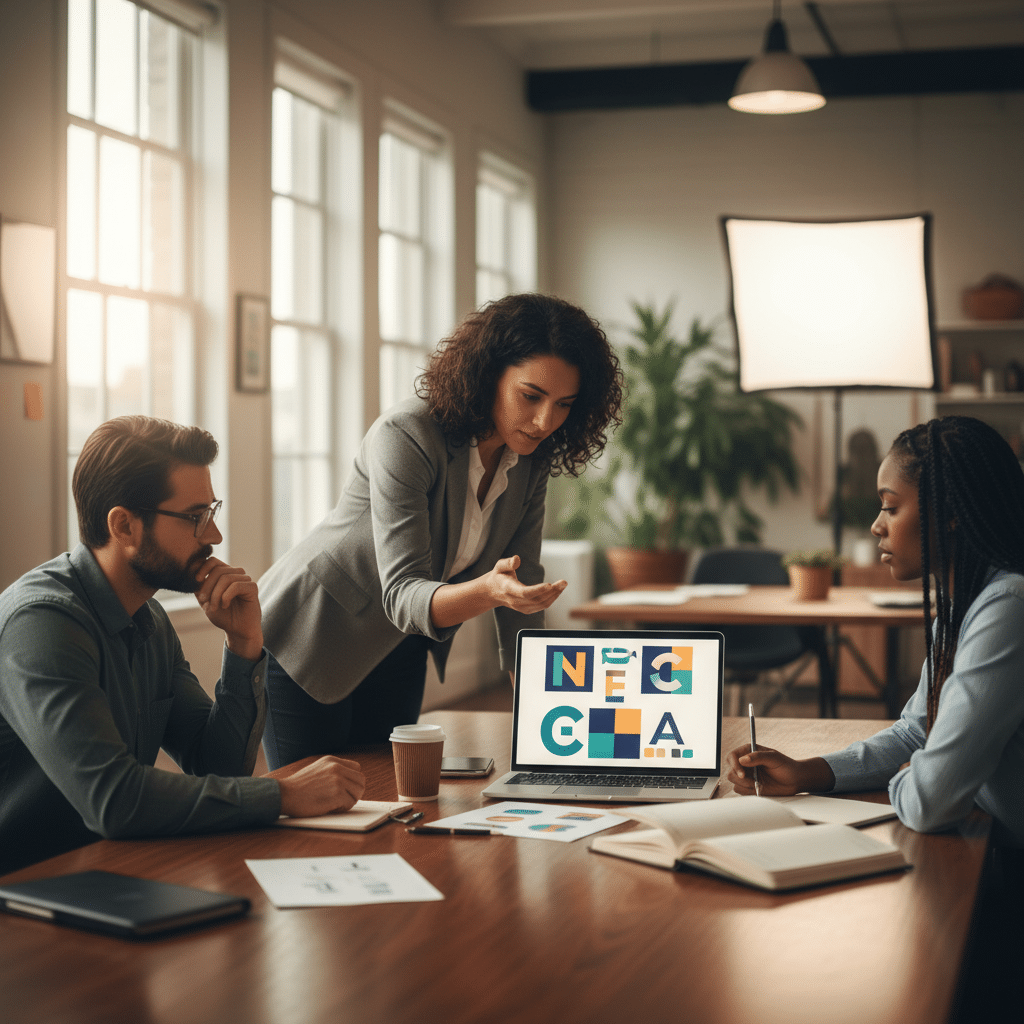
ฟอนต์เปลี่ยนแบรนด์! จิตวิทยาฟอนต์ที่ SME ต้องเลือกให้เป็น
การเลือกใช้ฟอนต์ไม่ใช่เพียงเรื่องของความสวยงามทางสายตา แต่เป็นเครื่องมือเชิงกลยุทธ์ที่ส่งผลกระทบโดยตรงต่อการรับรู้ของลูกค้า การตัดสินใจเลือก ฟอนต์เปลี่ยนแบรนด์! จิตวิทยาฟอนต์ที่ SME ต้องเลือกให้เป็น จึงเป็นศาสตร์ที่ผู้ประกอบการไม่ควรมองข้าม เพราะฟอนต์เปรียบเสมือน ‘น้ำเสียง’ ที่แบรนด์ใช้สื่อสารบุคลิกภาพ ค่านิยม และสร้างความน่าเชื่อถือในใจของผู้บริโภคได้ตั้งแต่แรกเห็น
แก่นสำคัญของจิตวิทยาฟอนต์
- ฟอนต์มีอิทธิพลต่ออารมณ์: รูปแบบของตัวอักษรสามารถกระตุ้นความรู้สึกที่แตกต่างกัน เช่น ความหรูหรา ความเป็นมิตร หรือความทันสมัย ซึ่งส่งผลต่อพฤติกรรมของผู้บริโภคโดยไม่รู้ตัว
- สร้างการจดจำและบุคลิกภาพ: ฟอนต์ที่เป็นเอกลักษณ์และสอดคล้องกับตัวตนของแบรนด์ ช่วยให้ลูกค้าสามารถจดจำแบรนด์ได้ง่ายขึ้นท่ามกลางคู่แข่งจำนวนมาก
- ยกระดับความน่าเชื่อถือ: การเลือกฟอนต์ที่เหมาะสมกับประเภทธุรกิจ สามารถเพิ่มความน่าเชื่อถือและความเป็นมืออาชีพให้กับแบรนด์ได้อย่างมีนัยสำคัญ
- สื่อสารคุณค่าของแบรนด์: ฟอนต์แต่ละประเภทมีความหมายแฝงที่สามารถสะท้อนถึงแก่นแท้และจุดยืนของแบรนด์ได้ เช่น ความสำเร็จ ความซื่อสัตย์ หรือความเป็นธรรมชาติ
ความสำคัญของจิตวิทยาฟอนต์ต่อแบรนด์ SME
สำหรับธุรกิจขนาดกลางและขนาดย่อม (SME) ที่มีทรัพยากรจำกัด การสร้างแบรนด์ให้แข็งแกร่งและเป็นที่จดจำคือความท้าทายที่สำคัญ จิตวิทยาฟอนต์ (Font Psychology) เข้ามามีบทบาทในฐานะเครื่องมือทางการตลาดที่ทรงพลังและคุ้มค่า เพราะฟอนต์คือองค์ประกอบแรกๆ ที่ลูกค้าสัมผัส ไม่ว่าจะผ่านโลโก้ บรรจุภัณฑ์ เว็บไซต์ หรือสื่อโฆษณาต่างๆ การเลือกฟอนต์ที่ถูกต้องสามารถสร้างความประทับใจแรกที่ยอดเยี่ยม และสื่อสารตัวตนของแบรนด์ออกไปได้อย่างชัดเจน
ฟอนต์ไม่ได้ทำหน้าที่เพียงแค่แสดงข้อความ แต่ยังทำหน้าที่ควบคุมการรับรู้และอารมณ์ของผู้ชมไปพร้อมกัน ฟอนต์ที่ดูหรูหราอาจทำให้ลูกค้ารู้สึกว่าสินค้ามีคุณภาพสูงและยินดีที่จะจ่ายในราคาที่แพงขึ้น ในทางกลับกัน ฟอนต์ที่ดูเป็นมิตรและเข้าถึงง่ายอาจช่วยสร้างความสัมพันธ์ที่ดีกับลูกค้าในธุรกิจบริการได้ ดังนั้น การทำความเข้าใจในศาสตร์นี้จึงเปรียบเสมือนการถือกุญแจสำคัญในการไขประตูสู่หัวใจของลูกค้าและสร้างความได้เปรียบในการแข่งขัน
การเลือกฟอนต์เปรียบเสมือนการเลือกเสื้อผ้าให้กับแบรนด์ หากเลือกได้เหมาะสมก็จะช่วยเสริมสร้างบุคลิกภาพให้น่าดึงดูดและน่าเชื่อถือ แต่หากเลือกผิด ก็อาจทำลายภาพลักษณ์ทั้งหมดได้ในพริบตา
ถอดรหัสความรู้สึกผ่านประเภทฟอนต์
ฟอนต์แต่ละประเภทมีโครงสร้างและลักษณะเฉพาะตัวที่ส่งผลต่อการตีความและความรู้สึกของผู้รับสาร การทำความเข้าใจความหมายทางจิตวิทยาของฟอนต์แต่ละกลุ่ม จะช่วยให้ SME สามารถเลือกใช้ฟอนต์ที่สื่อสารบุคลิกของแบรนด์ได้อย่างตรงจุด
ฟอนต์ Serif: สัญลักษณ์แห่งความน่าเชื่อถือและความหรูหรา
ฟอนต์ Serif คือฟอนต์ที่มี “ขีด” หรือ “เชิง” เล็กๆ อยู่ที่ปลายของตัวอักษร เป็นรูปแบบฟอนต์ที่มีประวัติศาสตร์ยาวนานและมักถูกใช้ในสื่อสิ่งพิมพ์แบบดั้งเดิม เช่น หนังสือพิมพ์ หรือหนังสือนวนิยาย ด้วยเหตุนี้ ฟอนต์กลุ่ม Serif จึงมักจะสื่อถึงความรู้สึก น่าเชื่อถือ, เป็นทางการ, หรูหรา, และ มีคุณภาพสูง แบรนด์ที่ต้องการสร้างภาพลักษณ์ที่ดูภูมิฐาน มั่นคง และเป็นที่ยอมรับ มักจะเลือกใช้ฟอนต์ประเภทนี้ ตัวอย่างเช่น ฟอนต์ Cotford Display Regular ที่ช่วยเสริมสร้างความสัมพันธ์และความไว้วางใจให้กับแบรนด์ได้เป็นอย่างดี
เหมาะกับธุรกิจ: แบรนด์แฟชั่นระดับสูง, ธุรกิจบริการที่เน้นความเป็นมืออาชีพ (เช่น สำนักงานกฎหมาย), สินค้าลักชัวรี, ธุรกิจโรงแรม, หรือสถาบันการเงิน
ฟอนต์ Sans-Serif: เสียงสะท้อนของความทันสมัยและความเรียบง่าย
“Sans” เป็นภาษาฝรั่งเศส แปลว่า “ไม่มี” ดังนั้น Sans-Serif จึงหมายถึงฟอนต์ที่ “ไม่มีเชิง” นั่นเอง ฟอนต์ประเภทนี้มีลักษณะที่ดูสะอาดตา เรียบง่าย และทันสมัย ทำให้เป็นที่นิยมอย่างสูงในยุคดิจิทัล โดยเฉพาะบนหน้าจอคอมพิวเตอร์และสมาร์ทโฟน ฟอนต์ Sans-Serif สื่อถึงความ ทันสมัย, ก้าวหน้า, เข้าถึงง่าย, และ ซื่อสัตย์ ฟอนต์ในกลุ่มนี้ยังแบ่งย่อยได้อีก เช่น Geometric Sans-Serif อย่าง Gilroy Bold ที่มักจะสื่อถึงความเป็น ของแท้ และ ความสำเร็จ ได้อย่างชัดเจน
เหมาะกับธุรกิจ: บริษัทเทคโนโลยี, สตาร์ตอัป, แบรนด์เสื้อผ้ากีฬา, ธุรกิจที่ต้องการสื่อสารความเป็นธรรมชาติและเรียบง่าย, หรือแบรนด์ที่ต้องการภาพลักษณ์ที่ดูเป็นมิตรและไม่ซับซ้อน
ฟอนต์ตัวเขียน (Script Fonts): ความอบอุ่นและเอกลักษณ์เฉพาะตัว
ฟอนต์ตัวเขียนมีลักษณะเลียนแบบลายมือของมนุษย์ ทำให้เกิดความรู้สึกที่เป็นส่วนตัวและมีเอกลักษณ์สูง ฟอนต์กลุ่มนี้สามารถสื่อถึงความ อบอุ่น, ความสง่างาม, ความคิดสร้างสรรค์, และ ความเป็นมืออาชีพ ในบางบริบท อย่างไรก็ตาม ควรใช้ฟอนต์ประเภทนี้อย่างระมัดระวัง โดยมักจะใช้เป็นฟอนต์สำหรับหัวข้อหรือข้อความสั้นๆ เพื่อเน้นย้ำ มากกว่าการใช้กับเนื้อหาจำนวนมาก เพราะอาจทำให้อ่านยากได้
เหมาะกับธุรกิจ: ธุรกิจบริการที่เน้นความสัมพันธ์ส่วนตัว (เช่น ร้านดอกไม้, การ์ดเชิญ), ร้านอาหารที่ต้องการบรรยากาศอบอุ่น, แบรนด์ที่เกี่ยวข้องกับงานฝีมือ หรือใช้เป็นลายเซ็นบนโลโก้
ลักษณะทางกายภาพของฟอนต์: ความหนาและความบาง
นอกเหนือจากประเภทของฟอนต์แล้ว ความหนา (Weight) ของตัวอักษรก็มีผลทางจิตวิทยาเช่นกัน
- ฟอนต์หนา (Bold): สื่อถึงความ มั่นใจ, เข้มแข็ง, โดดเด่น และ ความแน่วแน่ เหมาะสำหรับแบรนด์ที่ต้องการสร้างผลกระทบที่ชัดเจน หรือต้องการสื่อถึงพลังและความแข็งแกร่งของผลิตภัณฑ์
- ฟอนต์บาง (Light/Thin): สื่อถึงความ อ่อนโยน, ความละเมียดละไม, ความหรูหรา และ ความเรียบง่าย เหมาะสำหรับธุรกิจที่เกี่ยวข้องกับความสวยความงาม, สุขภาพ, หรือสินค้าที่ต้องการเน้นความนุ่มนวลและประณีต
| ประเภทฟอนต์ | ลักษณะความรู้สึก/ภาพลักษณ์ | เหมาะกับธุรกิจตัวอย่าง |